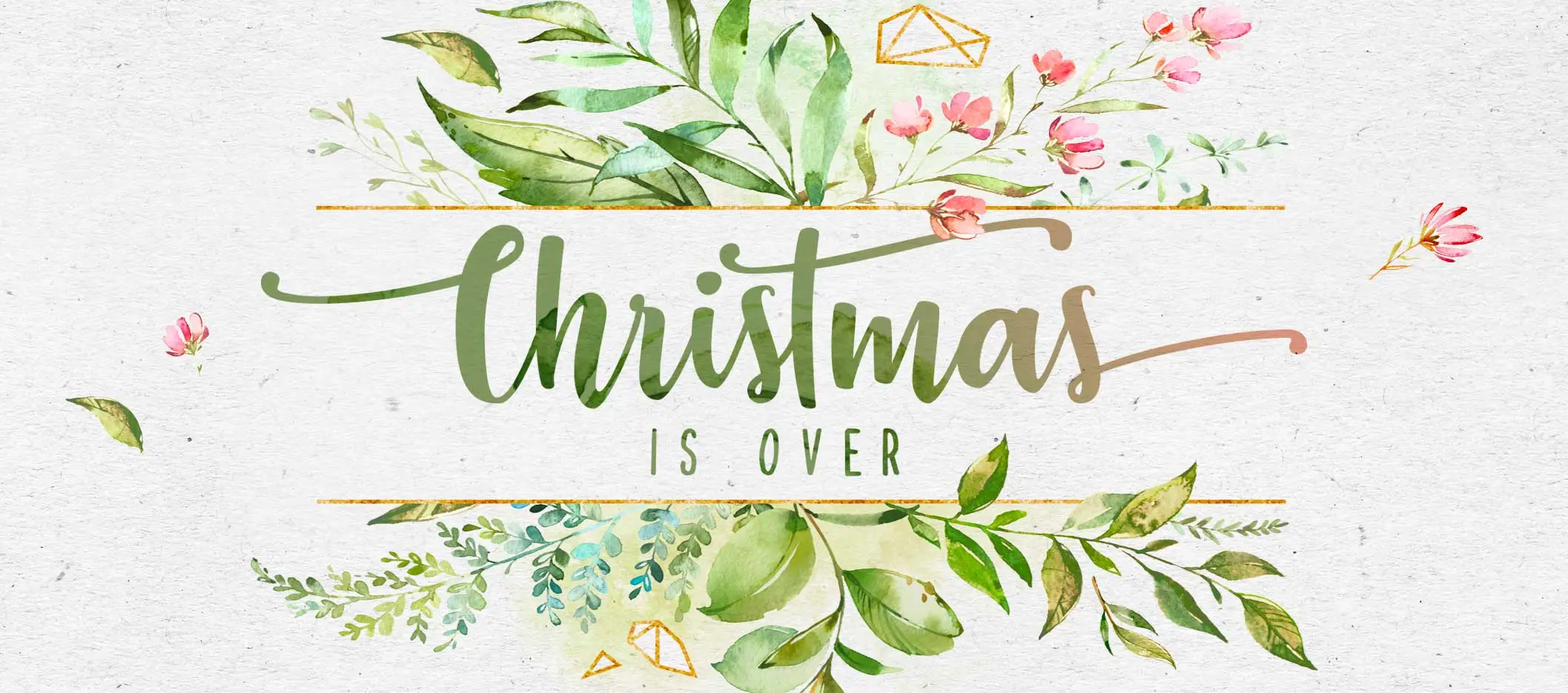
Introduzimos Strawberry Blossom Font! Desenvolvida e compartilhada pela StereoType, esta é uma fonte script casual e elaborada. Strawberry Blossom é perfeita para qualquer necessidade de design: desde logotipos até anúncios modernos, t-shirts personalizadas ou capas de livros. A versão comercial completa inclui um grande conjunto de alternativas, além de uma fonte adicional totalmente integrada. Perfeito para qualquer trabalho que precise de letras feitas à mão. Strawberry Blossom é uma ótima escolha para sua próxima criação gráfica.